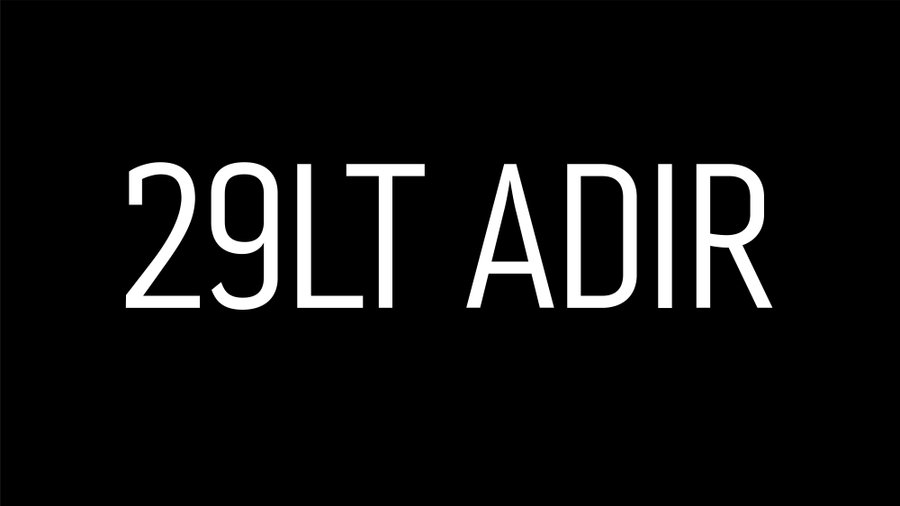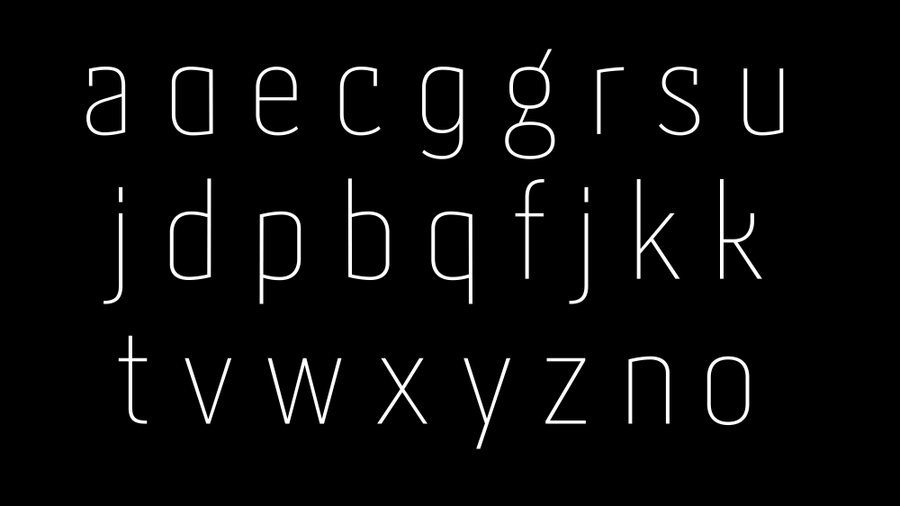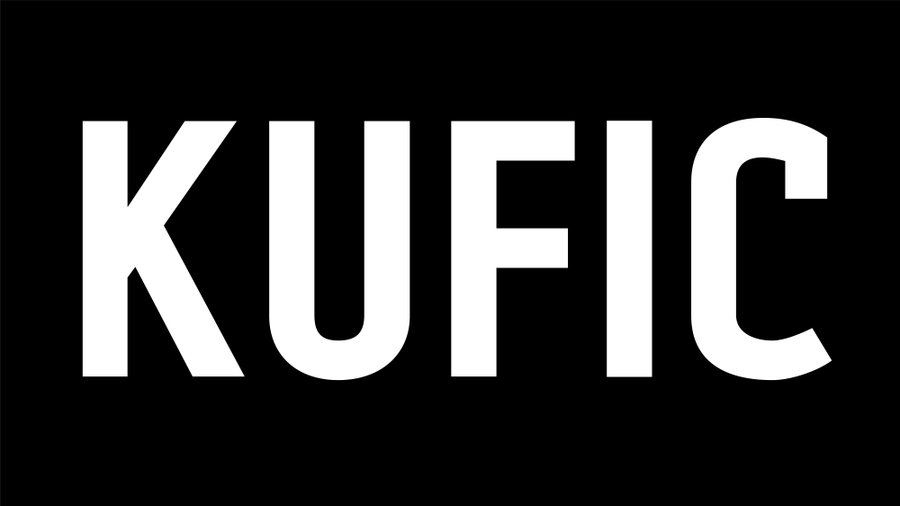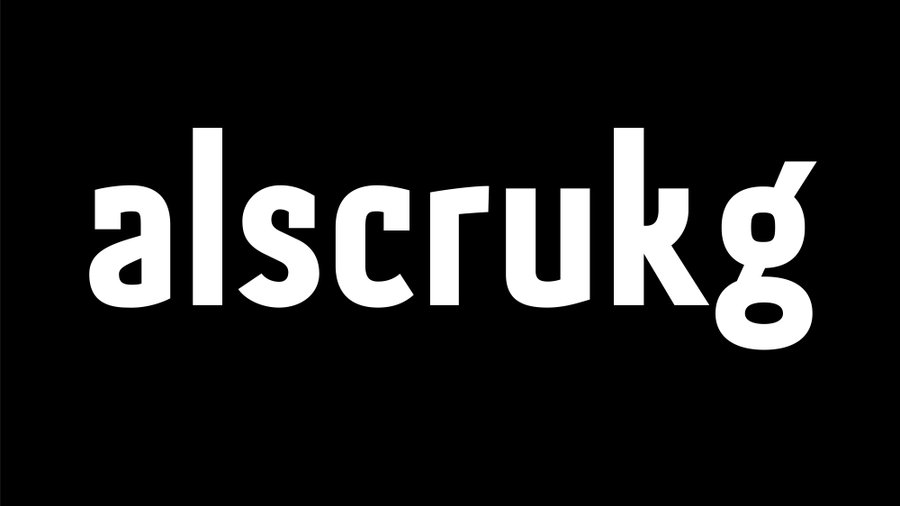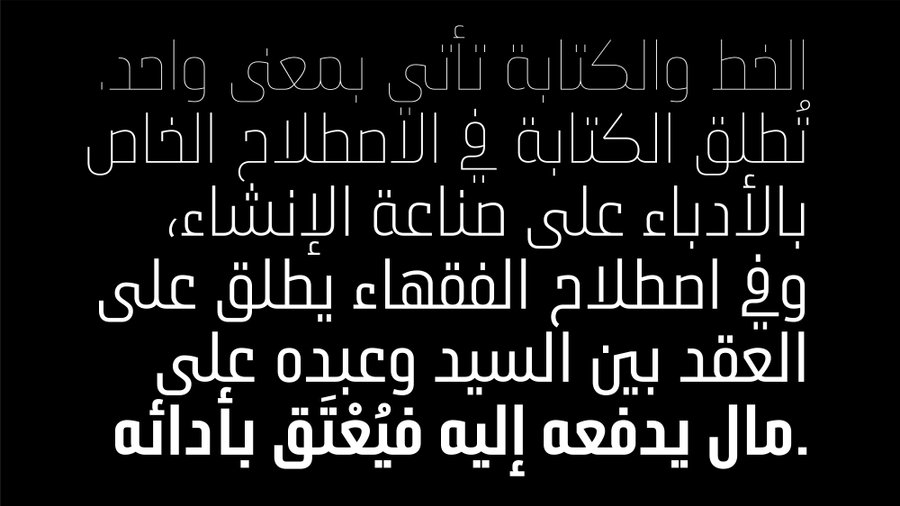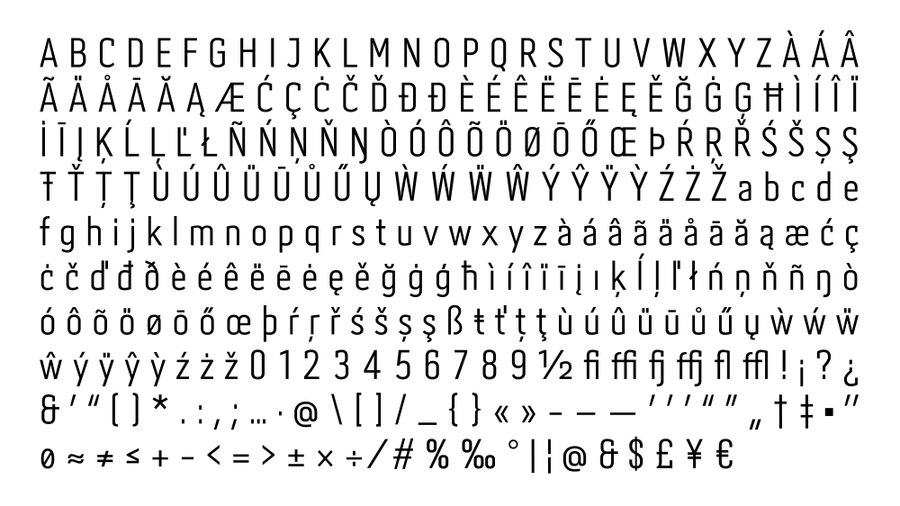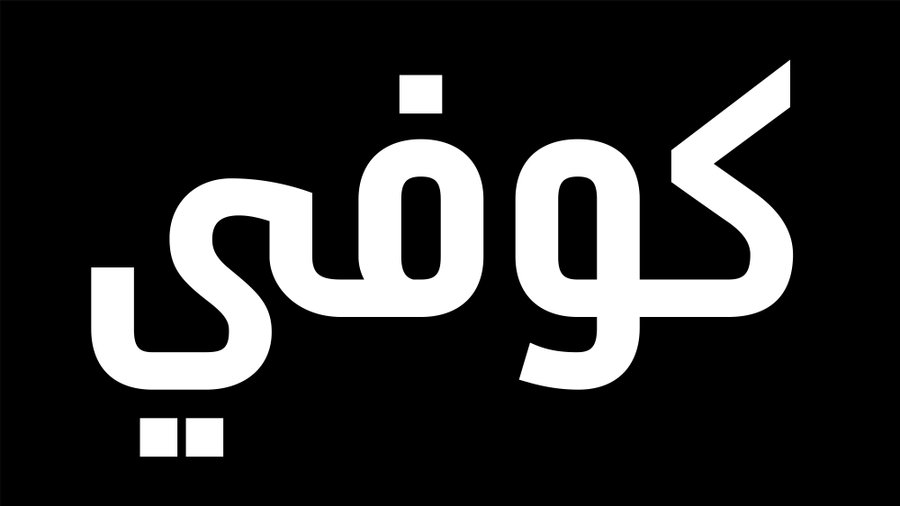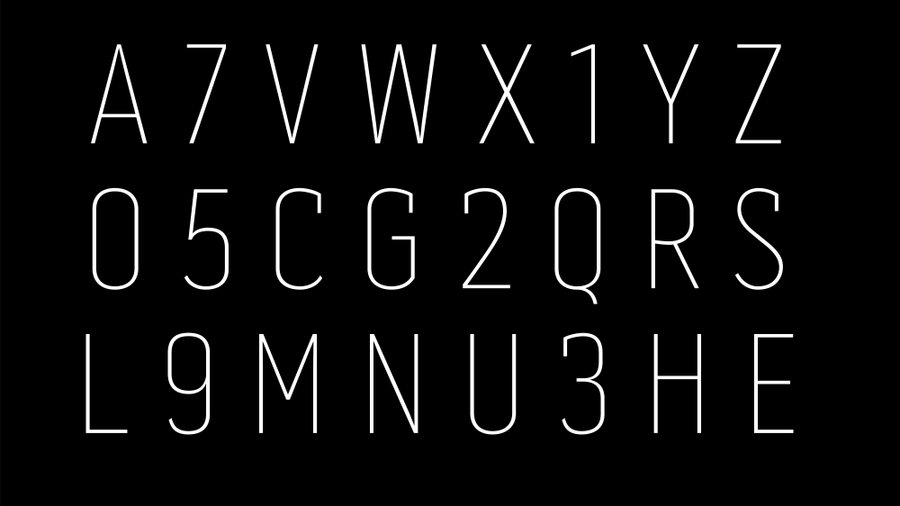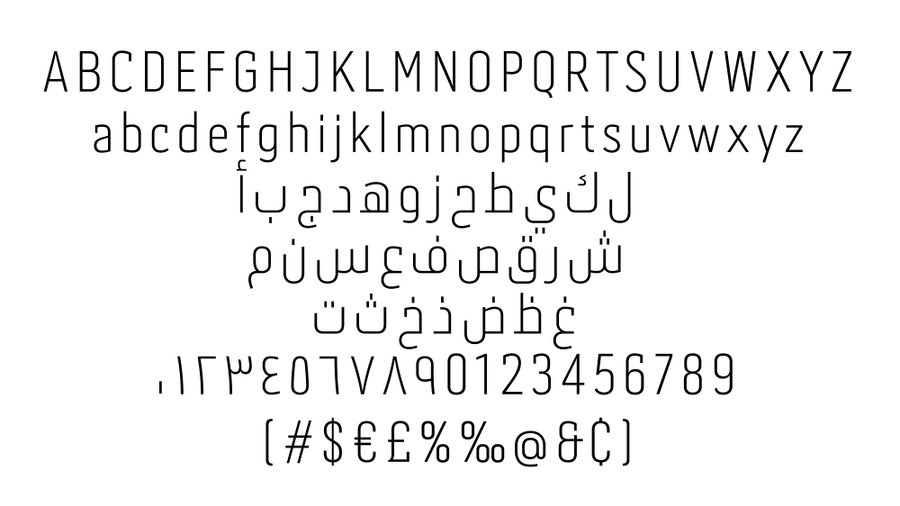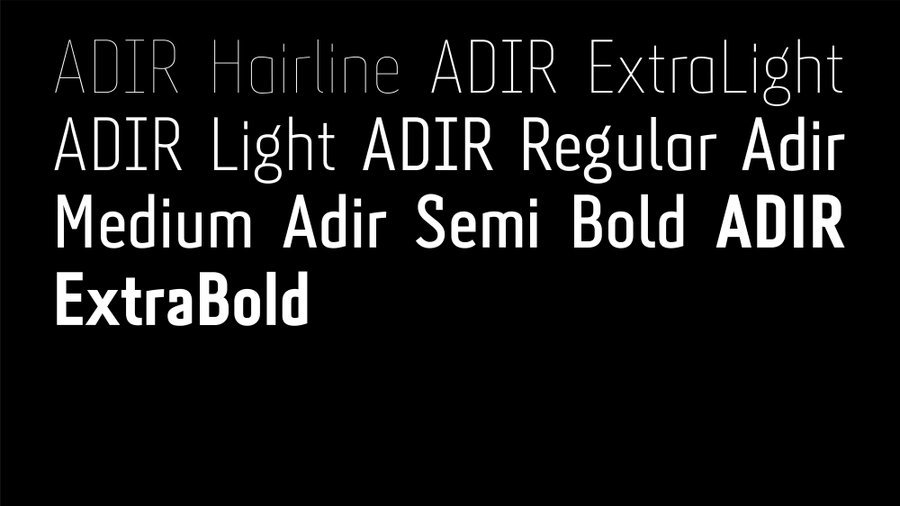
Adir
29LT Adir, une fonte multilingue condensée, moderne, dessinée avec un contraste faible. Le contraste entre ses formes géométriques et ses contre-formes douces traduit une sensation robuste et solide dans les graisses épaisses et une sensation élégante et distinguée dans les graisses légères. Les formes de lettres arabes ont été conçues sur la base du style Kufique avec une inspiration de style Naskh pour améliorer l'élégance et la lisibilité, tandis que le latin est un style géométrique de type Sans Sérif.
Les langues arabe et latine ont été créées simultanément et se sont mutuellement influencées tout en préservant les caractéristiques de chaque script. Bien que condensé ne soit pas un trait de script arabe, l’influence de la structure géométrique du Kufique sur ses formes confère aux lettres condensées une harmonie parfaite et une lecture aisée.